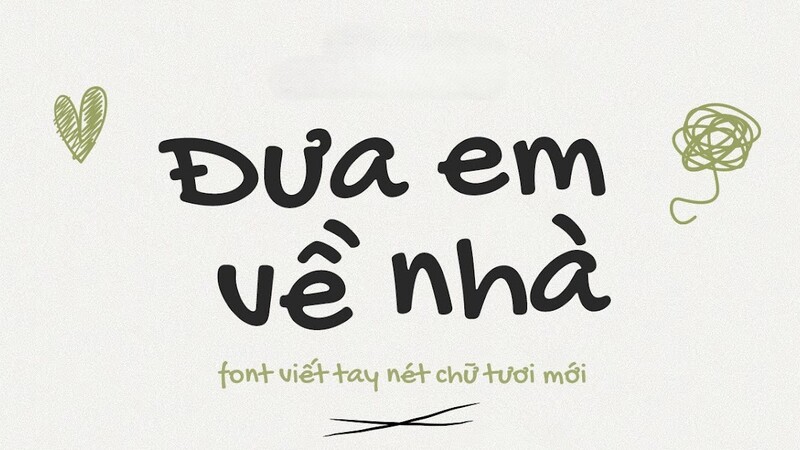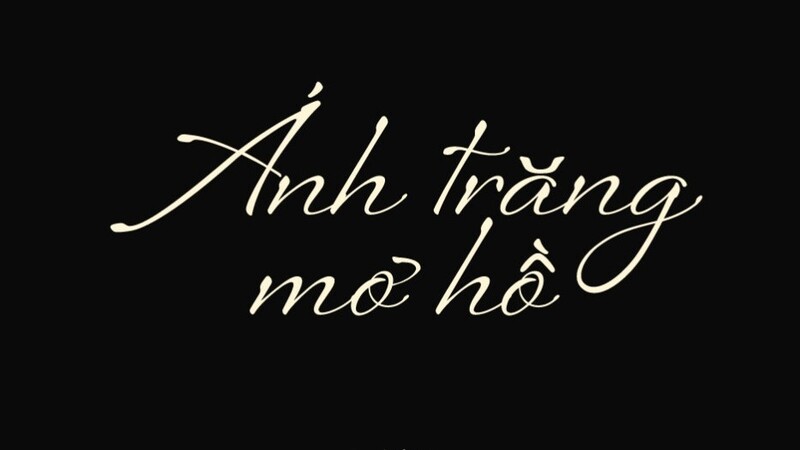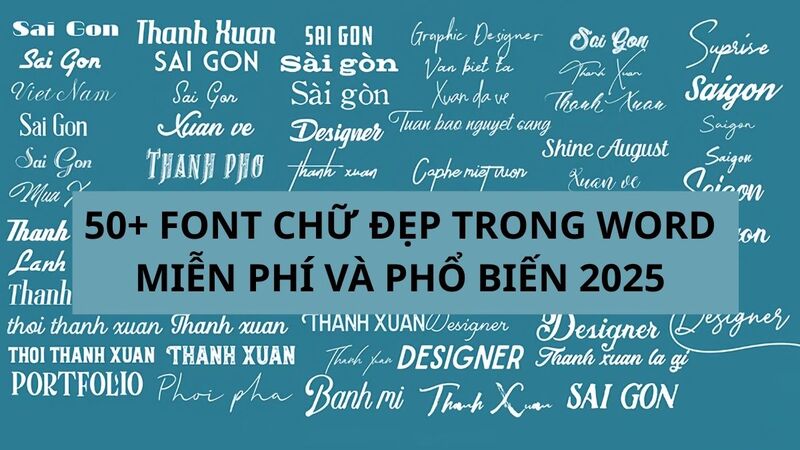
- Font chữ đẹp là yếu tố quan trọng tạo nên vẻ thẩm mỹ và cá tính cho văn bản.
- Có nhiều công cụ online và app miễn phí hỗ trợ tạo chữ kiểu nhanh chóng.
- Kiểu chữ đặc biệt như in đậm, nghiêng, in hoa được sử dụng nhiều trên Facebook, Instagram, TikTok.
- Vẽ chữ thủ công giúp tăng tính nghệ thuật và sáng tạo cho tiêu đề, trang trí.
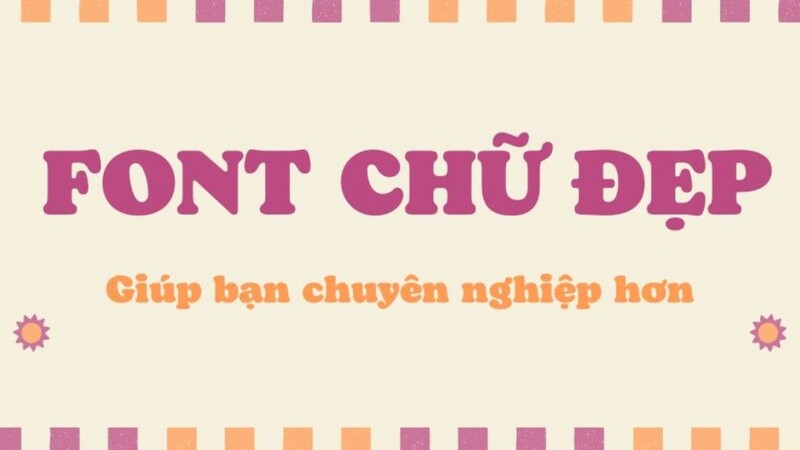
Giới thiệu chung Chữ kiểu và Font chữ đẹp
Chữ kiểu và font chữ đẹp là những yếu tố không thể thiếu trong thiết kế hiện đại, giúp nội dung trở nên nổi bật, truyền cảm hứng và gắn kết người đọc. Chọn đúng kiểu chữ không chỉ làm tăng tính thẩm mỹ mà còn thể hiện rõ cá tính, phong cách cá nhân hoặc thương hiệu.
Font chữ đẹp là những bộ chữ có thiết kế độc đáo, hài hòa về tỷ lệ, dễ đọc và phù hợp với mục đích sử dụng như thiết kế poster, thiệp mời, bài đăng mạng xã hội hoặc đơn giản là làm đẹp văn bản thường ngày. Trong khi đó, chữ thường nhấn mạnh đến sự sáng tạo, biến tấu hình dáng chữ nhằm tăng sức hút thị giác hoặc tạo điểm nhấn cá tính cho từng thông điệp.
Phân biệt chữ kiểu, font chữ và typography:
- Font chữ: Là bộ ký tự có cùng kiểu dáng, kích thước và định dạng, ví dụ Arial, Time New Roman.
- Chữ kiểu: Đề cập đến cách biến tấu, trang trí, hoặc tạo hiệu ứng đặc biệt cho chữ, có thể dựa trên một font chữ gốc.
- Typography: Là nghệ thuật sắp xếp chữ (bao gồm font, kiểu, kích cỡ, khoảng cách) để truyền tải thông điệp hiệu quả và đẹp mắt nhất.
Lịch sử phát triển: Từ những kiểu chữ cổ điển như Serif, Sans-serif thời kỳ in ấn, đến hàng ngàn chữ đẹp hiện đại ngày nay, sự phát triển của font chữ luôn song hành với công nghệ và nhu cầu thẩm mỹ. Các bộ font chữ đẹp không chỉ phục vụ in ấn mà còn đóng vai trò quan trọng trên website, mạng xã hội và các ứng dụng kỹ thuật số.
Tại sao cần sử dụng chữ đẹp? Một kiểu chữ ấn tượng giúp tăng khả năng ghi nhớ, tạo khác biệt cho thương hiệu hoặc cá nhân, đồng thời tạo cảm xúc mạnh mẽ cho người xem. Đặc biệt trong thời đại mạng xã hội, chữ đẹp là vũ khí giúp bài đăng của bạn trở nên viral và nổi bật hơn bao giờ hết.
Công cụ và Cách Tạo Chữ Kiểu/Font Chữ Độc Đáo
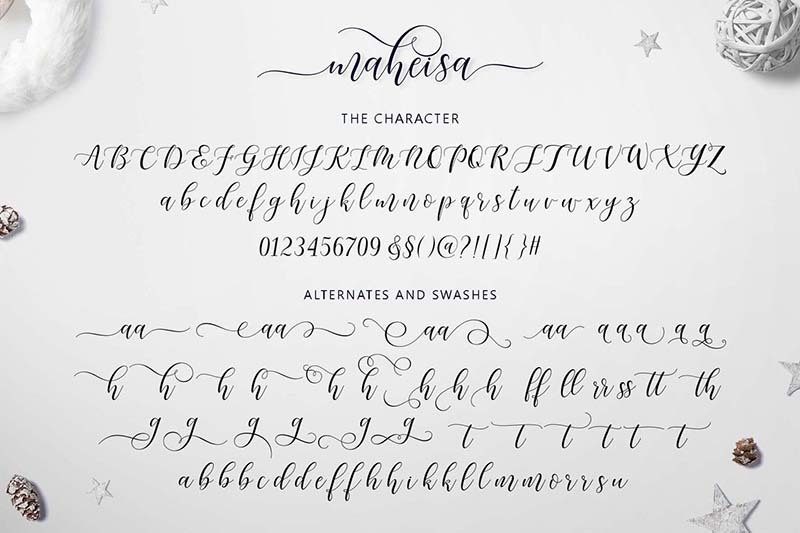
Việc tạo font chữ đẹp và tạo chữ kiểu online chưa bao giờ dễ dàng đến thế nhờ các công cụ hiện đại. Bạn có thể tùy ý sáng tạo, biến đổi chữ viết thường ngày thành những kiểu chữ nghệ thuật độc đáo chỉ với vài thao tác đơn giản.
Hướng dẫn tạo font chữ đẹp, tạo chữ kiểu:
- B2: Nhập văn bản cần chuyển đổi, chọn chữ bạn thích (in đậm, nghiêng, gạch chân, kiểu nghệ thuật, kiểu cute…)
Các trang web viết font chữ đẹp online:
- YayText: Đổi chữ in đậm, nghiêng, gạch chân, kiểu văn bản đặc biệt.
- Fonts for Instagram: Chuyên các chữ cho Instagram, đa dạng style hiện đại.
- Lingojam: Tạo font chữ nghệ thuật, font chữ cute, font lạ mắt.
- CoolSymbol: Thêm biểu tượng, icon vào chữ cực dễ thương.
App tạo chữ kiểu trên điện thoại:
- Fonty, Stylish Text, Phonto: Dễ dàng viết nhiều chữ khác nhau, chèn vào ảnh hoặc tin nhắn.
- Hỗ trợ đa dạng định dạng, có thể sử dụng trực tiếp trên bàn phím điện thoại.
Mẹo tạo chữ đẹp nhanh: Luôn thử nhiều kiểu chữ khác nhau để tìm ra style phù hợp. Kết hợp biểu tượng, ký tự đặc biệt tạo điểm nhấn. Nếu muốn nổi bật trên mạng xã hội, hãy ưu tiên các chữ dễ đọc, không quá lạ mắt nhưng vẫn cá tính.
Tip: Sử dụng chuyển đổi font chữ đẹp online giúp bạn tiết kiệm thời gian mà không cần cài đặt phần mềm phức tạp!
Tạo chữ kiểu trực tuyến với YayText và các công cụ tương tự
YayText là công cụ nổi bật giúp viết font chữ đẹp online tiếng Việt cực nhanh và dễ dàng. Bạn chỉ cần nhập văn bản vào ô, lựa chọn kiểu chữ (in đậm, nghiêng, gạch chân, bong bóng, nghệ thuật…) và sao chép kết quả.
Hướng dẫn từng bước:
- Truy cập yaytext.com.
- Nhập nội dung bạn muốn đổi font vào ô “Your Text”.
- Chọn kiểu chữ trong danh sách (ví dụ: Bold, Italic, Bubble, Smallcaps,…).
- Nhấn “Copy” bên cạnh kiểu chữ bạn thích và dán vào nơi sử dụng (Facebook, Zalo, Instagram,…).
Ưu điểm:
- Hỗ trợ tiếng Việt, giữ nguyên dấu tiếng Việt khi chuyển đổi.
- Nhiều lựa chọn kiểu chữ đặc biệt, phù hợp mọi mục đích.
- Không cần đăng ký tài khoản, không quảng cáo gây phiền.
Các công cụ tương tự YayText:
- Lingojam: Viết chữ lạ, chữ cute, chữ nghệ thuật.
- Fonts for Instagram: Đổi font cho bio, story Instagram.
- CoolSymbol: Nhiều ký tự đặc biệt, icon cho chữ thêm sinh động.
Lưu ý: Một số chữ chỉ hiển thị chuẩn trên thiết bị mới hoặc trình duyệt hiện đại.
Chữ đặc biệt & Ứng dụng trên các nền tảng mạng xã hội
Chữ đặc biệt như in đậm, nghiêng, in hoa,… đang là xu hướng nổi bật giúp các bài đăng, bình luận trên Facebook, Instagram, TikTok trở nên cá tính và cuốn hút hơn. Bạn có thể dễ dàng tạo chữ fb, chữ tiktok để đặt tên, hoặc chữ instagram chỉ trong vài giây.
8. Cách viết kiểu chữ in đậm, nghiêng trên Facebook là gì?
Hãy dùng các công cụ online như YayText, chọn kiểu chữ in đậm hoặc nghiêng, sau đó copy và dán vào status, bình luận hoặc tên Facebook. Đảm bảo chữ vẫn đọc được rõ ràng, giữ nguyên dấu tiếng Việt.